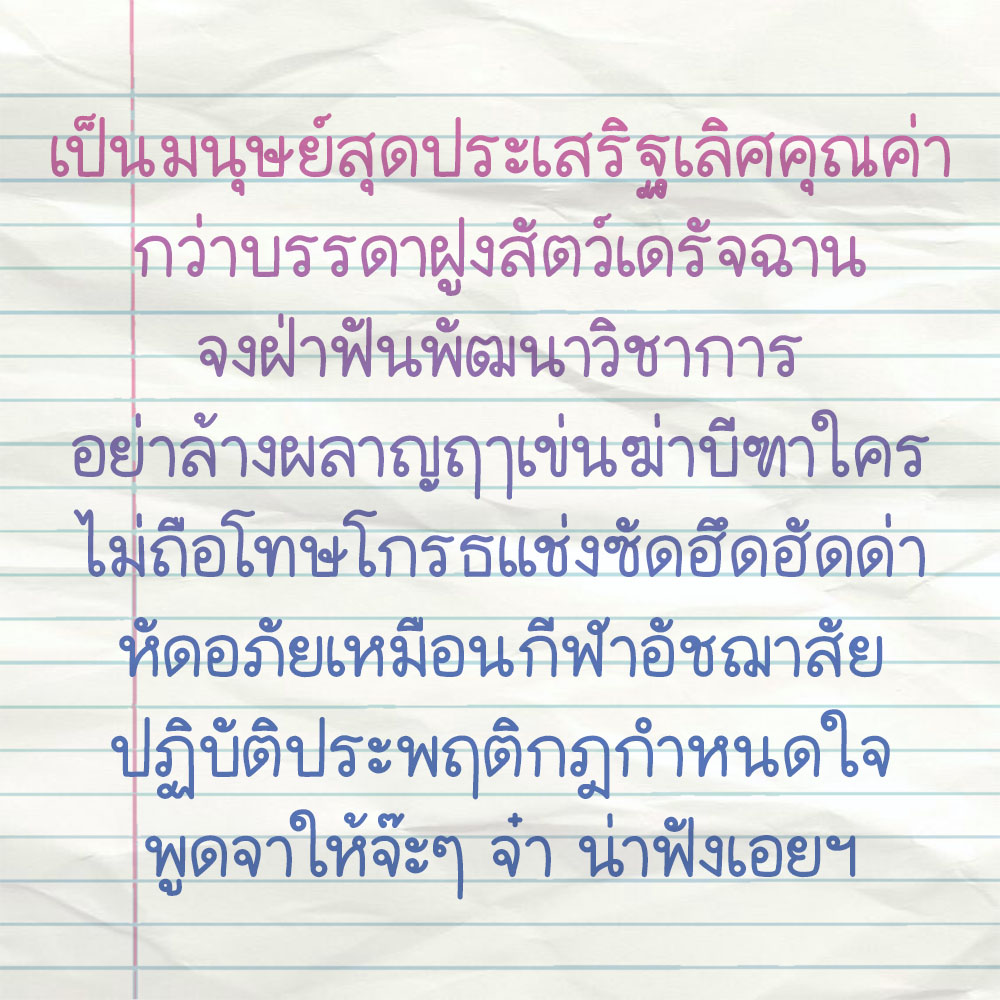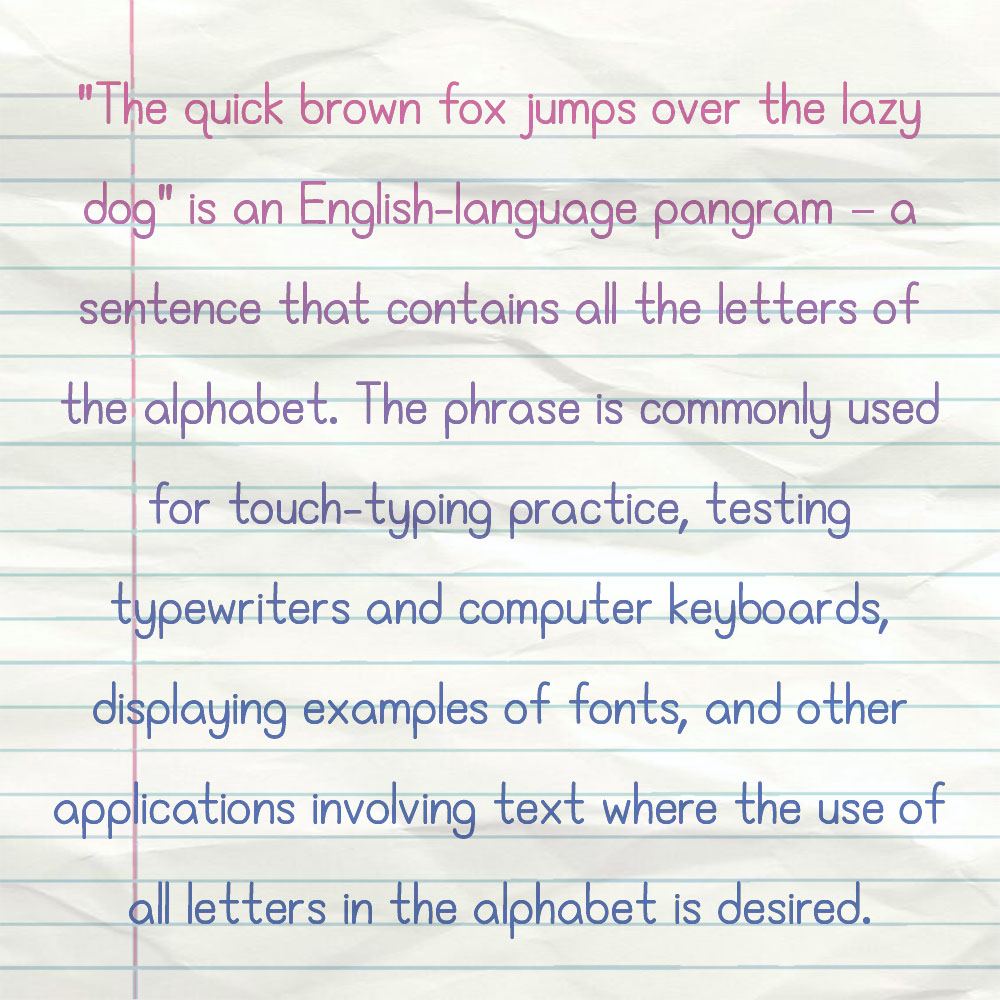
มือใหม่แนะนำตัวพร้อมขอคำแนะนำ
สวัสดีพี่ๆเพื่อนๆน้องๆนักออกแบบทุกท่านค่ะ ชื่อนิน่า เป็นเจ้าของฟอนต์ peana ค่ะ
สืบเนื่องจากว่าตัวน่าเองอยากได้ฟอนต์ลายมือเอาไว้สำหรับให้นักเรียนนักศึกษาจดโน้ตค่ะ
น่าจึงมีไอเดียเอาลายมือตัวเองมาประดิษฐ์ฟอนต์ขึ้นมาตัวหนึ่งชื่อว่า tembuntad(เต็มบรรทัด)
ทำอยู่หลายอาทิตย์ เลยอยากให้ลองโหลดกันไปใช้ และช่วยแนะนำอะไรกลับมาหน่อยค่ะ
ฟอนต์ลายมือน่ารักมากๆ เลย รบกวนแปะจองไว้ที่โพสต์นี้ได้เลยครับ คิวนานหน่อยนะครับช่วงนี้ :25: